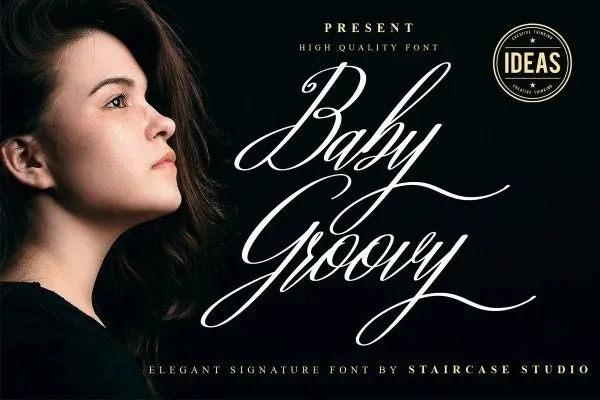
Baby Groovy Font – Download Grátis
Esta é uma fonte script moderna para letras e números escritas a mão. Ela foi criada pela Staircase Studio e é perfeita tanto para projetos pessoais quanto para trabalho profissional. Com sua elegante grife e estilo de escrita, ela se adequa perfeitamente para logotipos, criação de marcas, design de logos, arte de letras digitais, camisetas e roupas, cartazes, revistas, sinalizações e publicidade. Seja para qualquer necessidade de design que você possa imaginar, a Baby Groovy Font é uma escolha inteligente. A estética suave mas dinâmica faz dela um ícone para designers em busca de algo novo e interessante. Caso você esteja procurando por uma fonte moderna e criativa para dar ao seu design um toque pessoal ou jovial, esta pode ser sua melhor escolha.